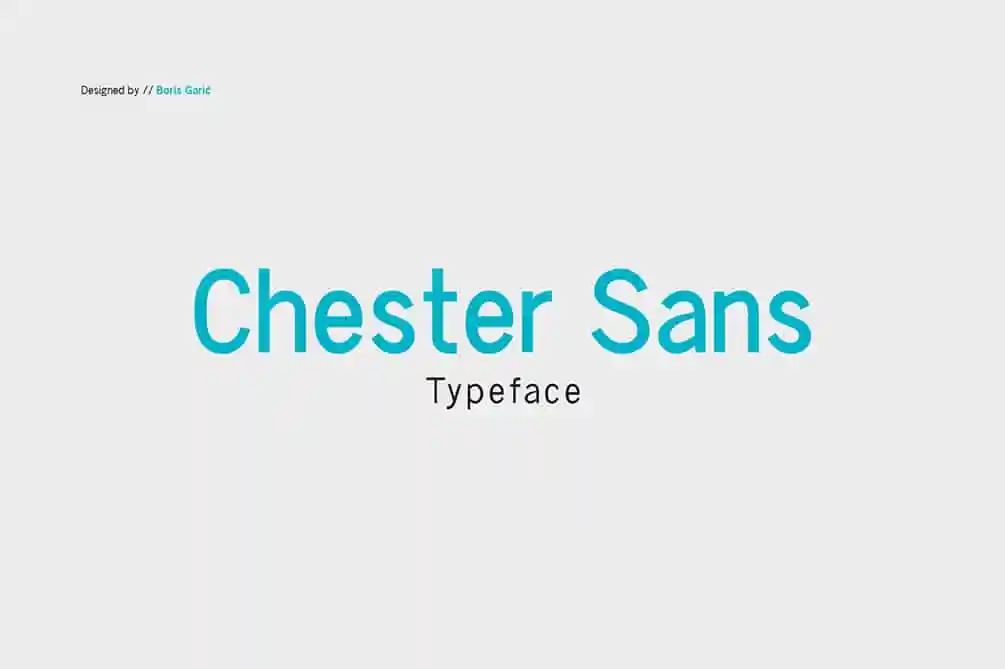
Chester Sans Font Family – Fonte Grátis
Chester Sans Font Family
Descobrimos uma nova família de fontes serifa simples chamada Chester Sans, projetada pelo designer Boris Garic. Nesta família de fontes, você encontrará diferentes iterações que se adaptam perfeitamente para textos diversos e variados — seja em relatórios anuais, livros ou menus. Chester Sans é uma excelente escolha para qualquer projeto que exija legibilidade e simplicidade no seu texto. Seu design leve e moderno permite que a fonte seja facilmente integrada em um amplo range de aplicações e formatos. Este tipo de fonte serifa é perfeitamente adaptável à necessidade de textos profissionais e convencionais, garantindo assim uma experiência visual harmoniosa em qualquer mídia ou plataforma. Adquirir Chester Sans não apenas adquiremos a liberdade de usar uma bela família de letras, mas também nos certificamos de que nossas publicações sejam consistentes e elegantes. Seja para o design gráfico profissional ou até mesmo para um projeto mais pessoal, esta família de fontes serifa é uma excelente escolha para tornar seus projetos ainda mais bonitos e agradáveis aos olhos do leitor.